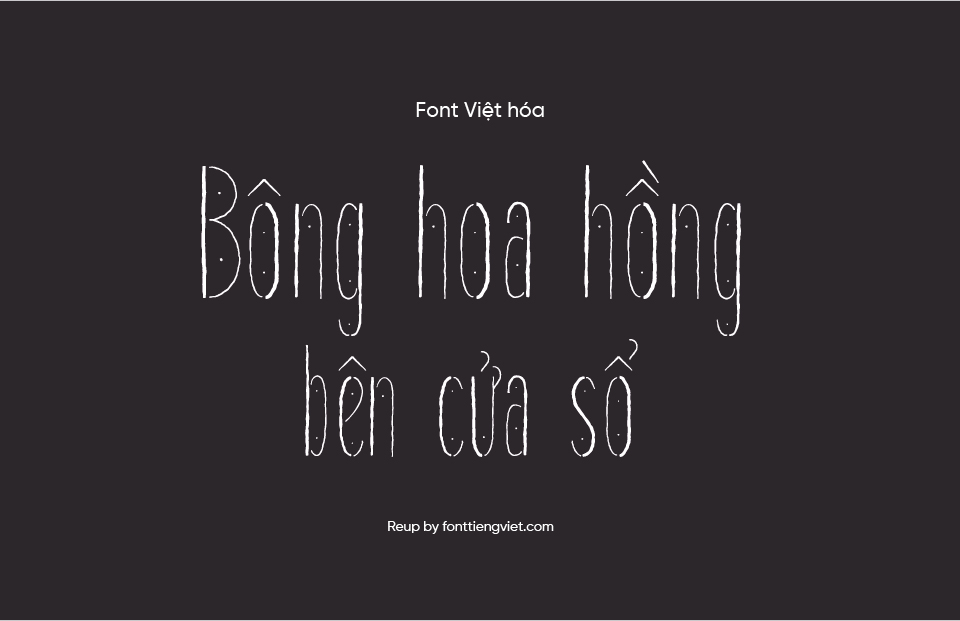
Trong kỷ nguyên số hóa, việc trình bày thông tin không chỉ dừng lại ở nội dung mà còn nằm ở tính thẩm mỹ. Đặc biệt đối với học sinh, sinh viên, hay các nhà thiết kế giáo dục, việc chọn một Font Chữ đẹp, dễ đọc và truyền cảm hứng là vô cùng quan trọng. Hôm nay, chúng ta sẽ đi sâu vào tìm hiểu một bộ font đang làm mưa làm gió trong cộng đồng thiết kế Việt Nam: Font Việt hóa MTD Good Day. Bộ font này không chỉ mang lại nét thanh lịch, hiện đại mà còn được tối ưu hóa hoàn toàn cho tiếng Việt, giúp các dự án học tập và cá nhân trở nên chuyên nghiệp hơn bao giờ hết. Đây chắc chắn là công cụ không thể thiếu cho những ai đang chuẩn bị các bài luận văn, kỷ yếu hoặc slide thuyết trình quan trọng, đặc biệt là trong giai đoạn nước rút của các kỳ thi tốt nghiệp.
Tại Sao Font Việt hóa MTD Good Day Lại Được Yêu Thích?
Sự phổ biến của font này không phải là ngẫu nhiên. Nó là kết quả của sự kết hợp hoàn hảo giữa tính thẩm mỹ cao (Aesthetics) và khả năng ứng dụng thực tế. Đối với học sinh cấp 3 hay sinh viên chuẩn bị cho các kỳ thi tốt nghiệp, việc sử dụng font MTD Good Day giúp bài làm hoặc tài liệu nghiên cứu của họ trở nên nổi bật mà vẫn giữ được sự trang trọng cần thiết, khác biệt hoàn toàn so với các kiểu chữ mặc định phổ biến.
Đặc Điểm Nổi Bật Về Kiểu Dáng (Styling)
MTD Good Day sở hữu phong cách Script (font viết tay) nhưng lại rất dễ đọc, không quá rườm rà. Các nét chữ mềm mại, bay bổng, tạo cảm giác thân thiện và tươi mới. Phiên bản Việt hóa đã giải quyết triệt để vấn đề lỗi hiển thị dấu tiếng Việt, vốn là rào cản lớn khi sử dụng các font nước ngoài. Các ký tự như ă, â, đ, ê, ô, ơ, ư được căn chỉnh tỉ mỉ, đảm bảo độ chính xác typography cao nhất. Điều này cực kỳ quan trọng khi bạn đang biên soạn tài liệu học tập chính thức, các bài báo cáo khoa học hoặc các poster thông báo cho trường học cần tính chuyên nghiệp cao.
Tính Ứng Dụng Cao Trong Giáo Dục
Từ việc thiết kế bìa sách giáo khoa, tạo tiêu đề cho các báo cáo khoa học, đến việc trang trí bằng khen hay chứng chỉ cuối khóa, Font Việt hóa MTD Good Day đều thể hiện sự linh hoạt đáng kinh ngạc. Khác với các font serif truyền thống nặng nề, font này mang lại hơi thở trẻ trung, rất phù hợp với các ấn phẩm hướng đến đối tượng học sinh, sinh viên, tạo ra sự hứng thú và giảm bớt sự khô khan trong tài liệu học tập. Đây là một công cụ mạnh mẽ giúp nâng cao chất lượng thị giác cho mọi dự án, từ cấp tiểu học cho đến các dự án nghiên cứu đại học.
Các Dự Án Sáng Tạo Nên Dùng Font Việt hóa MTD Good Day
Font này đặc biệt tỏa sáng trong các dự án cần sự cá nhân hóa và nghệ thuật cao. Đây là một số ý tưởng áp dụng thực tế cho các bạn học sinh chuẩn bị tốt nghiệp hay tham gia các hoạt động ngoại khóa, giúp bài dự thi của bạn đạt điểm cao về sự sáng tạo:
- Kỷ Yếu Học Sinh: Sử dụng font này cho các trích dẫn, tên gọi hoặc lời chúc để tăng thêm tính lãng mạn và kỷ niệm, làm nổi bật những khoảnh khắc đáng nhớ của tuổi học trò.
- Thiết Kế Poster Sự Kiện Trường: Font MTD Good Day rất thu hút khi làm tiêu đề cho các sự kiện văn nghệ, hội thảo hoặc câu lạc bộ, dễ dàng thu hút sự chú ý của cộng đồng học sinh.
- Slide Thuyết Trình Cao Cấp: Thay vì dùng các font mặc định nhàm chán, font này giúp bài thuyết trình của bạn (nhất là phần giới thiệu và kết luận) trở nên độc đáo và ghi điểm với giáo viên nhờ tính thẩm mỹ cao.
- Thiệp Mời Tốt Nghiệp: Không gì trang trọng và ấm áp hơn một tấm thiệp mời được viết bằng kiểu chữ bay bổng, tinh tế như MTD Good Day, thể hiện sự trân trọng đối với người nhận.
Tóm lại, Font Việt hóa MTD Good Day là một tài sản vô giá cho bất kỳ ai hoạt động trong lĩnh vực giáo dục, thiết kế học đường, hay chỉ đơn giản là muốn làm đẹp thêm cho tài liệu cá nhân. Với sự tối ưu hóa hoàn hảo cho tiếng Việt, tính linh hoạt cao và vẻ đẹp cuốn hút, đây là lựa chọn hàng đầu để nâng tầm chất lượng các dự án của bạn, từ bài tập về nhà đơn giản đến dự án thi tốt nghiệp phức tạp. Đừng ngần ngại khám phá và áp dụng bộ font tuyệt vời này ngay hôm nay. Việc lựa chọn một Font Chữ phù hợp chính là bước đầu tiên để tạo nên một tác phẩm thiết kế thành công. Hãy tải về và bắt đầu trải nghiệm sự khác biệt mà MTD Good Day mang lại!